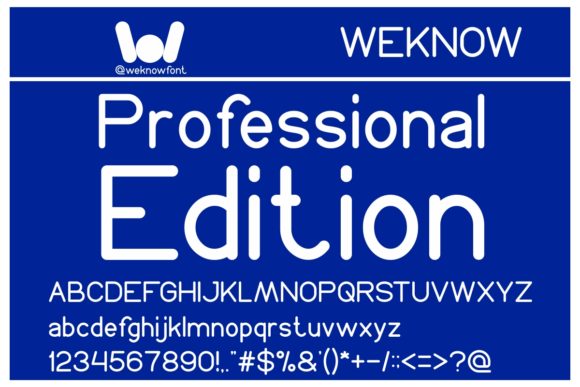
Professional Edition
Conçu avec précision, Professional Edition offre des vecteurs nets, une typographie fluide et une licence commerciale pour une tranquillité d'esprit.